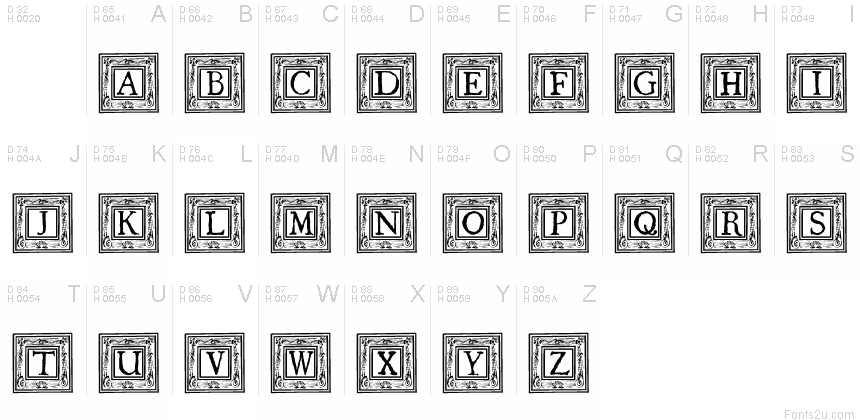
Qua Nauticale Initials No1 von Manfred Klein, inspiriert durch einen unbekannten Drucker aus dem Jahr 1678 und Paul Lloyd, ist eine kostenlose Schrift mit maritimen Initialen, die den Charme alter Bücher versprüht. Die Buchstaben sind in massive quadratische Rahmen eingebettet, verziert mit Muscheln, gewundenen Meeresbewohnern und ornamentalen Details. So wirkt das Alphabet weniger wie eine einfache gotische Schrift, sondern eher wie handgedruckte Initialen aus historischen Seefahrtsmanuskripten.
Diese kostenlose Schrift eignet sich hervorragend für Buchcover, Kapitelanfänge, Urkunden, Poster und Menüüberschriften, bei denen ein einzelner Buchstabe oder eine kurze Zeile von diesem maritimen Gravur-Stil profitieren soll. Sie ist ideal für Initialen, Monogramme und Titelkarten, da der Rahmen hier genauso viel Wirkung entfaltet wie der Buchstabe selbst.
Manfred Klein, unknown printer & Paul Lloyd, 1678 - 2004